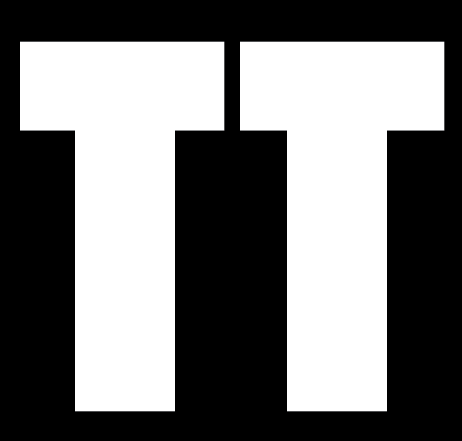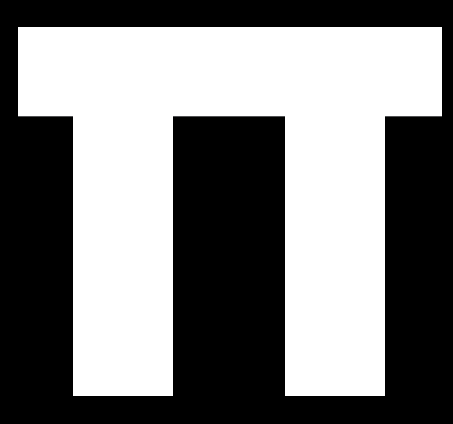
Abstand zwischen TT
mal wieder eine Basisfrage von mir:
wie soll man in diesem Fall Verfahren? den Abstand zwischen den Buchstaben vergrössern um zu vermeiden, daß sie sich oben berühren? Oder Berührung zu lassen, um Unten keinen zu grossen Abstand zu bekommen?
Es kommt ein wenig darauf an, wie der Rest der Schrift aussieht, bzw. wie gesetzt wird (9pt in einem Buch, oder auf 1m hoch als Logo? Eng oder weit?)
Bei Logo- und Schriftzug-Anwendungen würde ich sie wohl zusammenziehen wie im Bild (wenn der Rest ähnlich kompress gesetzt ist. Bei Text hingegen eher nicht.
Weitere Möglichkeit: Die beiden Arme die sich jetzt berühren dezent verkürzen, die Ts also asymmetrisch machen. Es entsteht ein Abstand zwischen den Armen, die Ts sind also einzeln erkennbar, gleichzeitig wird der Abstand zwischen den Buchstaben aber nicht zu groß, dass es optische Löcher reißt. Und da die Balken horizontal optisch Kontinuität erzeugen, dürfte auch die Asymmetrie kein großes Problem sein.
(Ich mach sowas grade Versuchsweise für eine meiner Schrift-Entwürfe – in jenem Fall klappt es.)
ich finde es grässlich wenn die zusammenhängen. Sieht aus wie ein kaputtes Pi oder eine erstaunlich gut erhaltene griechische Baustelle.
das mit den gekürzten Armen ist ein interessanter Ansatz. Bin auf das Ergebnis gespannt. :rockon: